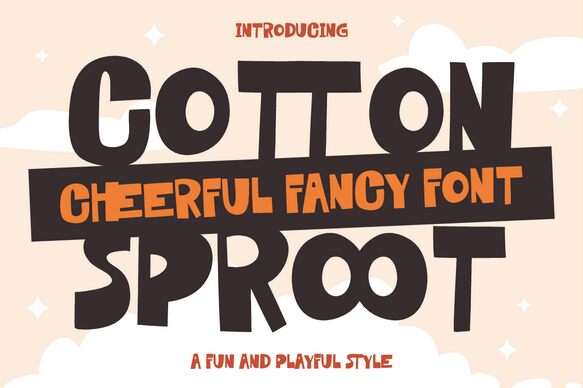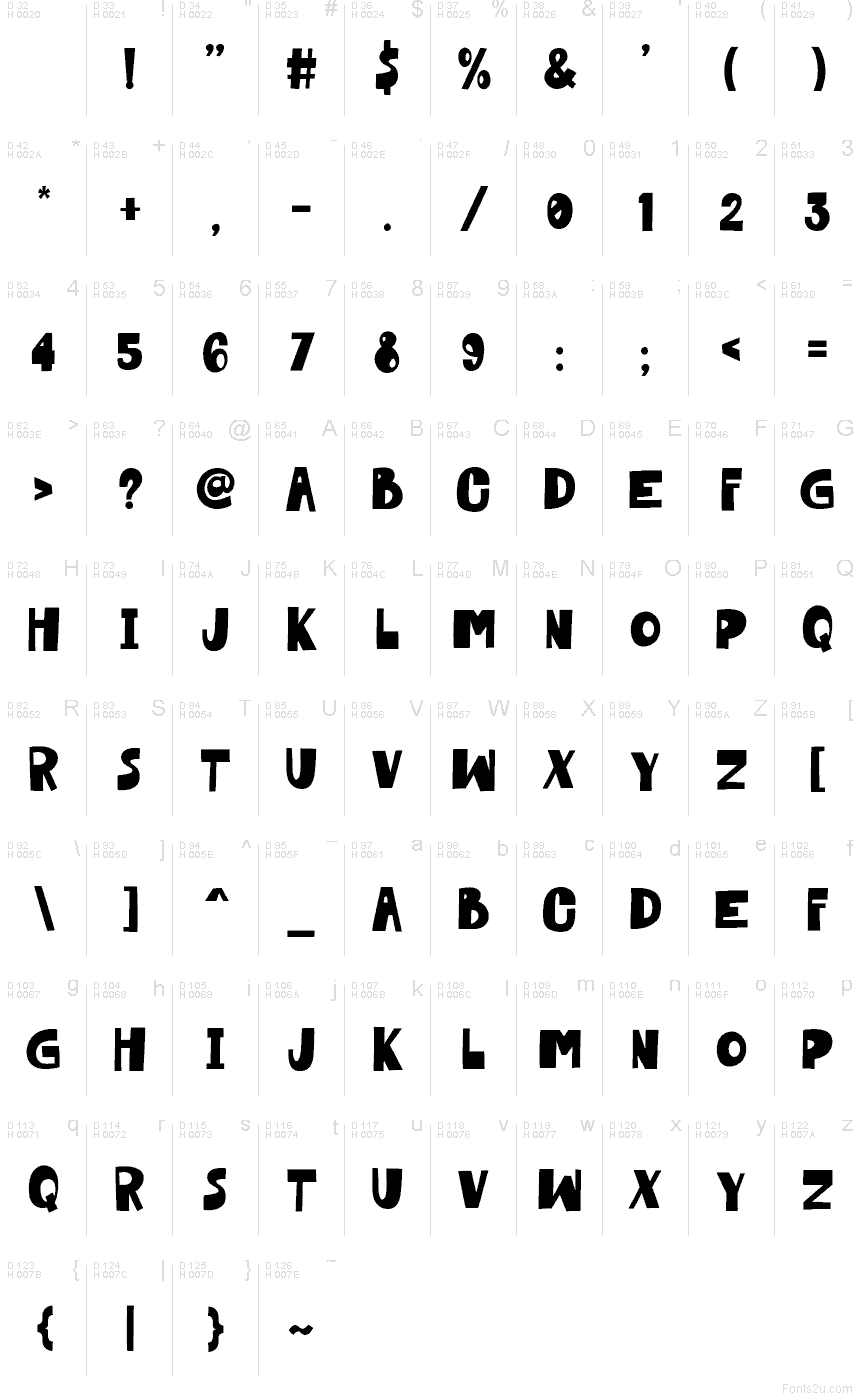
Cotton Sproot
Cotton Sproot, uma fonte display gratuita em estilo cartoon criada pela Shanaf Studio, aposta em letras grandes e arredondadas com topos robustos e quadrados, criando um ritmo divertido e levemente desajeitado. As formas são suaves, mas imponentes, com curvas amplas e verticais sólidas que dão às maiúsculas um ar de desenho animado alegre, fugindo de acabamentos excessivamente polidos.
É perfeita para branding de produtos infantis, embalagens de snacks, títulos de cartazes, capas de YouTube e cartões de título curtos, onde uma tipografia amigável e de grande impacto ajuda a definir o tom rapidamente. Como é uma fonte gratuita, também funciona muito bem para flyers de eventos escolares ou gráficos rápidos para redes sociais, especialmente quando você quer passar uma mensagem audaciosa, vibrante e descontraída.